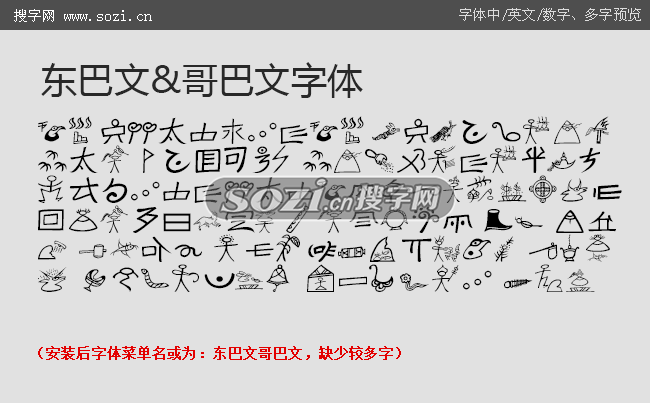
東巴文哥巴文字體
搜字網(wǎng)給大家提供一款東巴文哥巴文字體下載。東巴文、哥巴文,為中國(guó)納西族的文字。是一種原始的圖畫(huà)象形文字,主要為東巴教徒傳授使用,書(shū)寫(xiě)東巴經(jīng)文,故稱(chēng)東巴文。適合字體設(shè)計(jì)、包裝設(shè)計(jì)、海報(bào)設(shè)計(jì)等廣告設(shè)計(jì)場(chǎng)合使用。